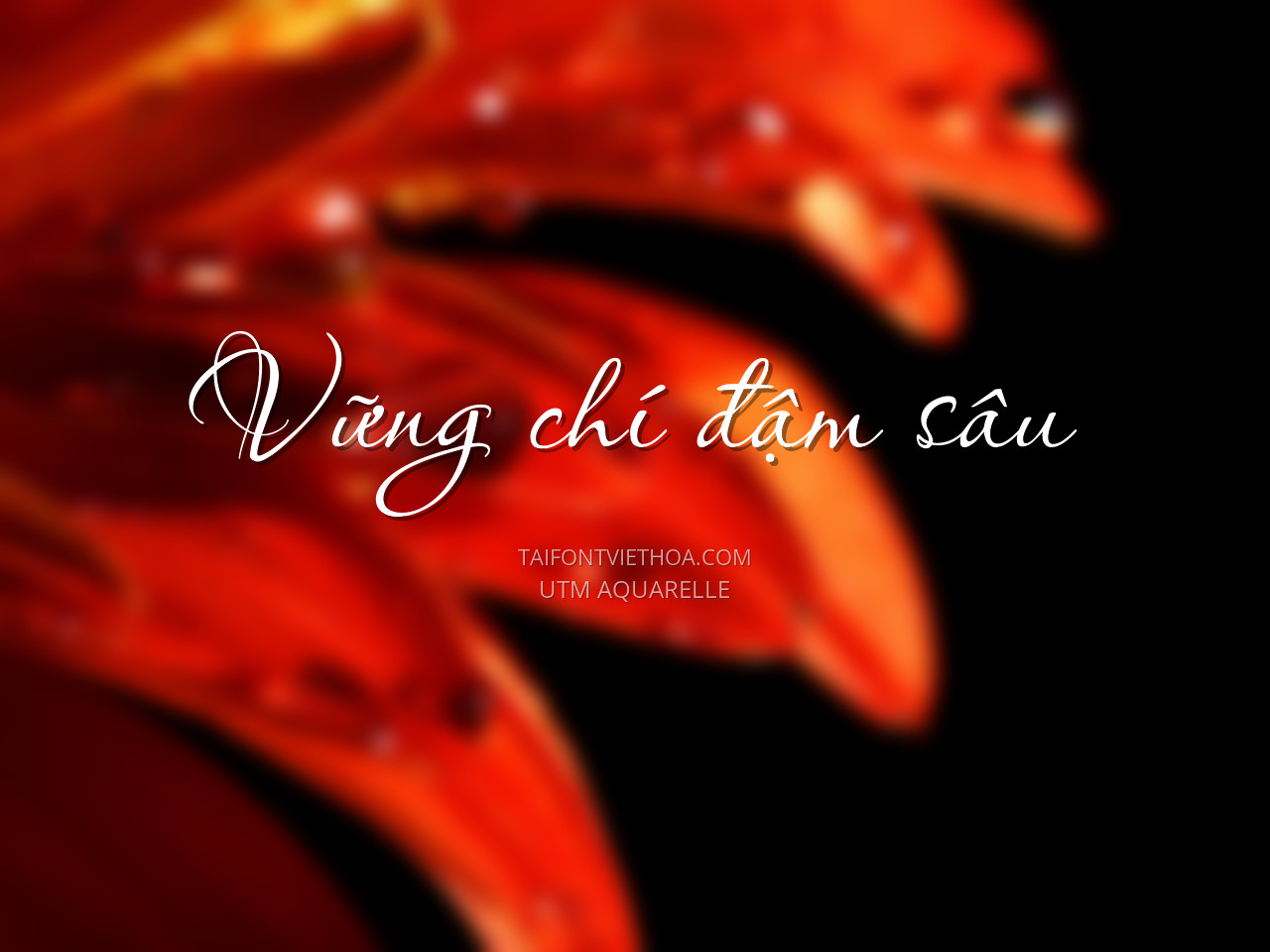
Font việt hóa UTM Aquarelle
Giới thiệu về font UTM Aquarelle
UTM Aquarelle là phiên bản Việt hóa của font Aquarelle – một kiểu chữ script mềm mại và bay bổng, được thiết kế bởi nhà thiết kế tài năng tại Pháp. Font gốc nổi bật với các nét chữ được mô phỏng theo nét cọ vẽ thủ công, tạo cảm giác tự nhiên và nghệ thuật. Phiên bản Việt hóa đã được hoàn thiện để hỗ trợ đầy đủ tiếng Việt cùng hơn 100 ngôn ngữ khác, giúp font dễ dàng ứng dụng trong nhiều dự án thiết kế sáng tạo và truyền cảm hứng.
Đặc điểm thiết kế và ứng dụng của UTM Aquarelle
UTM Aquarelle sở hữu cấu trúc chữ script với các đường nét mềm mại, uốn lượn tự nhiên, tạo nên sự bay bổng và duyên dáng cho từng ký tự. Font có độ tương phản nhẹ nhàng, thích hợp cho các thiết kế mang tính cá nhân hóa và nghệ thuật. Các ligature và ký tự thay thế đa dạng giúp tăng tính linh hoạt và sáng tạo cho người dùng.
Font rất phù hợp cho các ứng dụng như thiệp cưới, thiết kế bao bì mỹ phẩm, poster nghệ thuật, logo thương hiệu cá nhân, và các dự án sáng tạo đậm chất nghệ thuật. Ngành nghề phù hợp gồm: tổ chức sự kiện, thời trang, mỹ phẩm, nghệ thuật sáng tạo, quảng cáo cá nhân hóa và thiết kế nội thất.
Thiết kế: Lauren Ashpole
Việt hóa: Font DL